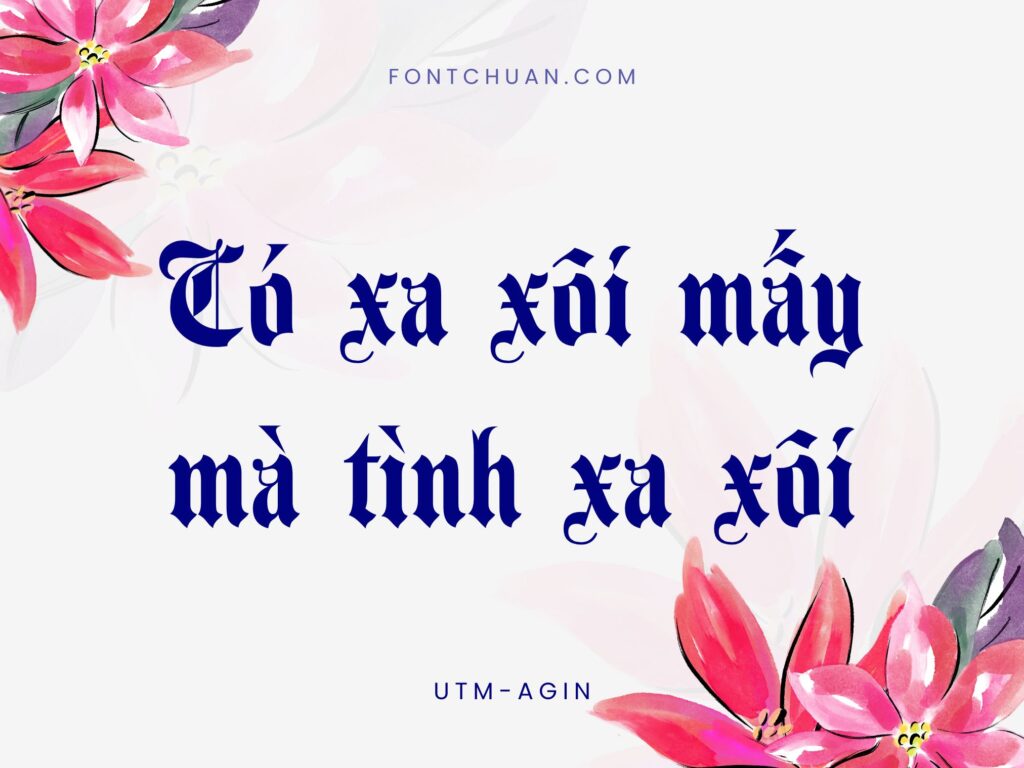
Font UTM Agin Việt Hóa
UTM Agin là một kiểu chữ mang phong cách Gothic cổ điển, được thiết kế bởi Michael Đinh Kiên và phát hành lần đầu vào năm 2001. Font sở hữu phong cách mạnh mẽ, cứng cáp và đầy cá tính, rất phù hợp với những thiết kế đòi hỏi tính chất thị giác rõ ràng. Với các chi tiết trang trí tinh xảo và độc đáo trên từng ký tự, UTM Agin còn được xem là một Font Decorative, giúp các tiêu đề, logo hoặc poster trở nên ấn tượng và thu hút hơn. Phiên bản này hỗ trợ đầy đủ tiếng Việt cùng với hơn 18 ngôn ngữ khác. Đây là một trong những font được thành viên Font Chuẩn sưu tầm và chọn lọc kỹ càng nhằm phục vụ cộng đồng thiết kế trong các ứng dụng mang hơi hướng cổ điển, mạnh mẽ và trang trọng.
UTM Agin nổi bật với các đường nét dày, góc cạnh, độ tương phản cao và tỷ lệ chữ được căn chỉnh đều đặn, dễ đọc ở cả kích thước lớn và nhỏ. Font đặc biệt phù hợp cho các ứng dụng như tiêu đề, logo, bìa sách, poster phim hoặc các ấn phẩm in ấn cần gây ấn tượng thị giác mạnh. Những ngành nghề như quảng cáo, bất động sản, giáo dục và công nghệ hoàn toàn có thể tận dụng UTM Agin để truyền tải thông điệp rõ ràng và chuyên nghiệp trong thiết kế.